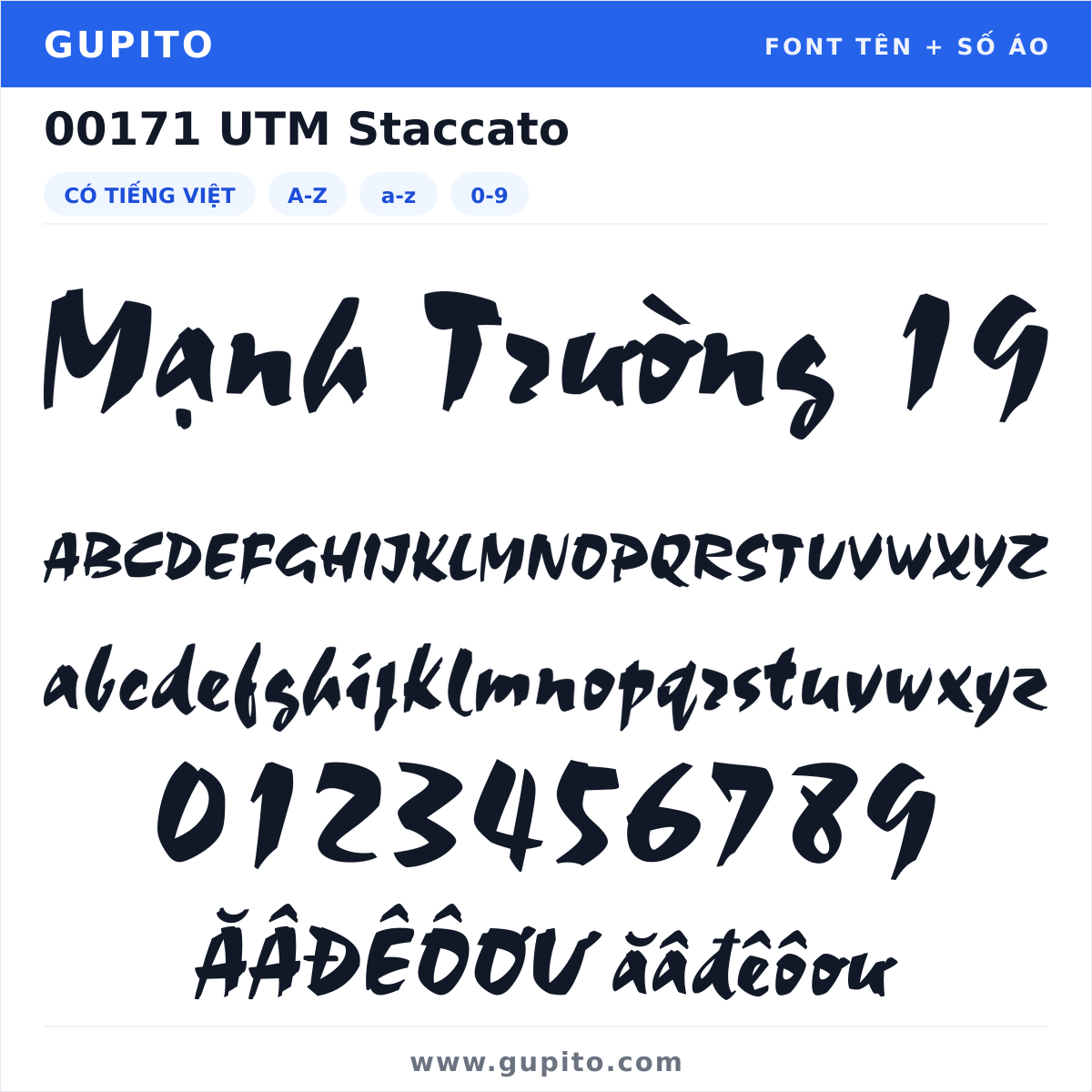
UTM Staccato
UTM Staccato · Font UTM Staccato in tên áo, số áo, chữ tiếng Việt · nét cọ phóng khoáng · có tiếng Việt
Font UTM Staccato độc đáo, nét chữ phóng khoáng, có tiếng Việt, bảng số, phù hợp in tên áo bóng đá, áo lớp, quà tặng. Bộ chữ UTM Staccato dùng để in chuyển nhiệt lên áo đấu, áo lớp, áo nhóm và đồ thể thao theo yêu cầu. Kiểu dáng: nét cọ phóng khoáng. Font hỗ trợ tiếng Việt có dấu, gõ được tên riêng đầy đủ. Có đủ bộ chữ số để in số áo. Từ khoá liên quan: font utm staccato, font in ten ao, font in so ao, font tieng viet, font co tieng viet, font a-z, font 0-9, font chu thuong.